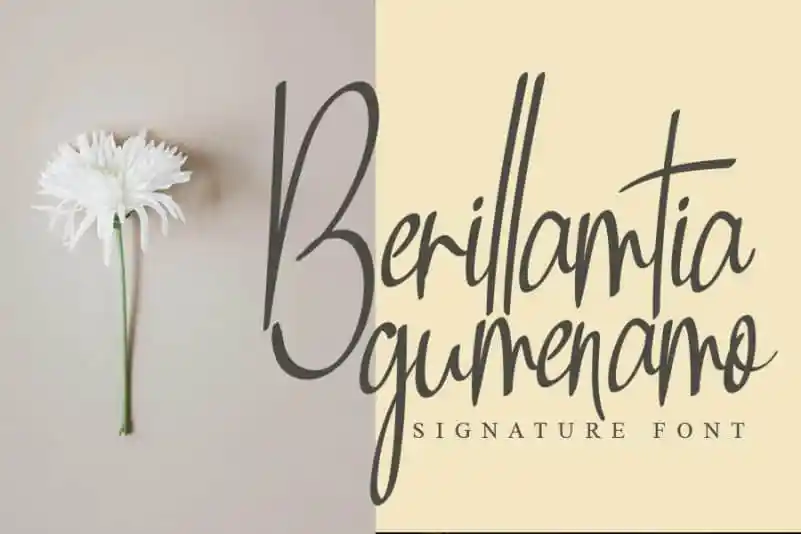
Berillamtia Handwritten Font – Download Grátis
A fonte Berillamtia Handwritten é uma criação moderna e divertida que surgiu usando um pincel pontilhado. Ela foi projetada para dar vida a seus trabalhos de logomarca, identidade visual, mídia social e até mesmo as suas próprias DIY projetos casuais. A fonte tem uma aparência limpa e com um toque peculiar que a torna perfeita para qualquer projeto criativo. Ideal tanto para empresas quanto para indivíduos, Berillamtia Handwritten é o tipo de fonte que vai deixar seu trabalho de design ainda mais especial. Com certeza vale a pena ter essa fonte em sua coleção de tipos de texto para dar um toque único e divertido aos seus projetos.